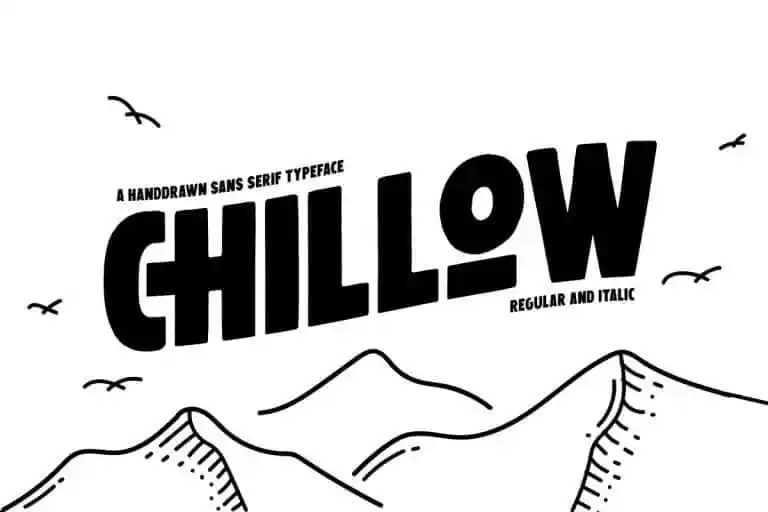
Chillow Display Font – Download Grátis
A Chillow Display Font é uma bela fonte retro que traz um toque de brincadeira e elegância. Foi projetada especificamente para ser usada em títulos, headlines e posters, tornando-a perfeita para qualquer execução vintage. Essa fonte bold e desenhada a mão está inspirada no estilo do design gráfico vintage dos anos 1940 à década de 1970. Concebida pelo designer Andika Setiawan, esta font é uma tipografia sans serif com um tom rugoso e vintage. Ela vem em duas estilos padrão e itálico, além de incluir alternativas de caracteres e ligaturas, garantindo que você tenha todas as ferramentas necessárias para criar designs vintage perfeitos. Chillow é a fonte ideal para logos, selos, tipografia e qualquer projeto que exija um toque vintage. Seja você um designer gráfico ou até mesmo uma pessoa criativa procurando por algum estilo retro em seu próximo projeto de design, Chillow Display Font será sua melhor escolha.